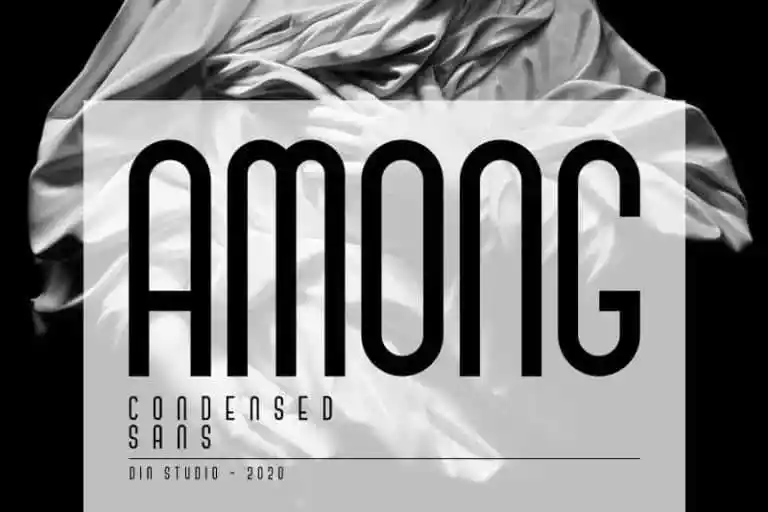
Among Sans Serif Font – Download Grátis
A Among Sans Serif Font é uma elegante tipografia sans serif que transmite classe e simplicidade ao mesmo tempo. Desenvolvida pelo Din Studio, esta fonte moderna combina linhas retas e leves para criar um resultado sofisticado. Perfeita tanto para uso em projetos profissionais quanto em elementos de marca, a Among Sans Serif é uma opção ideal para impressão, branding e até mesmo para textos quotes, onde suas letras apresentam nuances únicas e lindas. Ideal para quem busca uma fonte simples mas com um toque elegante, ela se destaca como uma escolha sólida em qualquer projeto de design gráfico.